公開: 2018-11-14技術の卓越性を考えると、手書きは間違いなく道端に落ちています。 ただし、まだかなりの魅力があり、慎重に選択されたレタリングフォントは、さまざまなニッチに最適な、より「作家的な」感覚を呼び起こすことができます。 良いニュースは、オンラインから選択できるオプションが何千もあるということです。
これを念頭に置いて、この投稿では15の最高のレタリングフォントを見て、それらがユニークである理由を分析します。 また、各フォントが無料かプレミアムかについても明確に説明します。
レタリングフォントはすべて、クラシックでエレガントなスタイルです。 ただし、間違ったものを選択すると、面倒に見えます。 そのため、各例の評価とレビューを調べて、この選択を15に絞り込みました。さらに、このリストは特定の順序ではないので、気になるレタリングフォントを自由に試してみてください。
1.金色の手
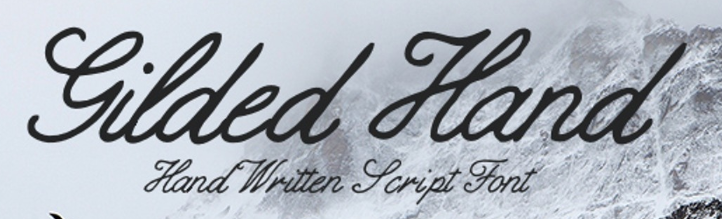
このリストの最初のフォントは文字通り手作業で作成されたものであり、これを見ると明らかです。 それは古い羊皮紙で場違いに見えない書体であり、華やかなスタイリングにもかかわらず、その筆記体の性質は読みやすく、4ドルで悪くはありません。
ただし、Gilded Handは小さいサイズでは少し読みにくい場合があるため、これはタイトルと見出しにのみ使用することをお勧めします。 ただし、サイズの小さい筆記体スクリプトは読みにくいことが多いため、これは予想されることです。
2.ボールペン
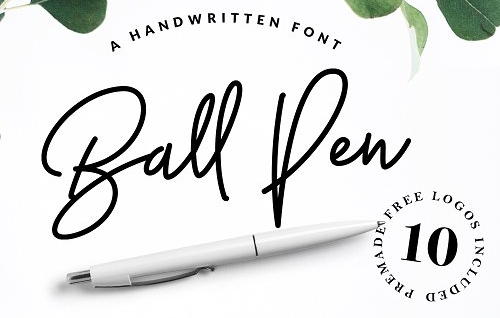
次に、ボールペンは手書きの「ヒップスター」スタイルのフォントで、クラシックとモダンの両方を同時に見ることができます。 私たちは特に白の見た目が大好きで、あなたのデザインに気楽なスタイルを与えることができます。
作者は、すばやく書き留められた署名を呼び出す方法を高く評価するかもしれませんが、これはヴィンテージのロゴで自宅にぴったりと見えると思います。 Gilded Handと同様に、これは超大型のタイトルや潜在的にコールアウトテキストなどのアプリケーションに使用することをお勧めします。
3.デイジードッグ
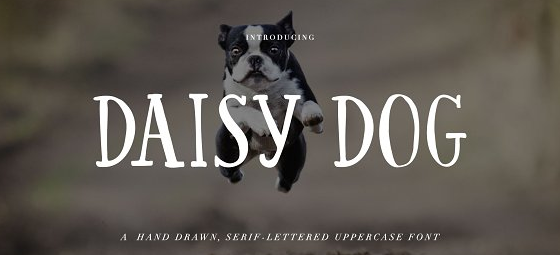
デイジードッグはヴィンテージ風で、このオールキャップスフォントは簡単にスタイリッシュです。 また、ヘッダー画像、タイトル、ロゴの優れたオプションとなるデザインにより、非常に読みやすくなっています。
ボールペンと同じように、このフォントも白で非常に上品に見えます。つまり、背景が暗いサイトでは、これを確認する必要があります。 デイジードッグはオールキャップスであるため、一般的な本文テキストには適していませんが、コールアウトやその他の目立つテキスト用の場所を見つけることができる可能性があります。
4.作成者タイプ
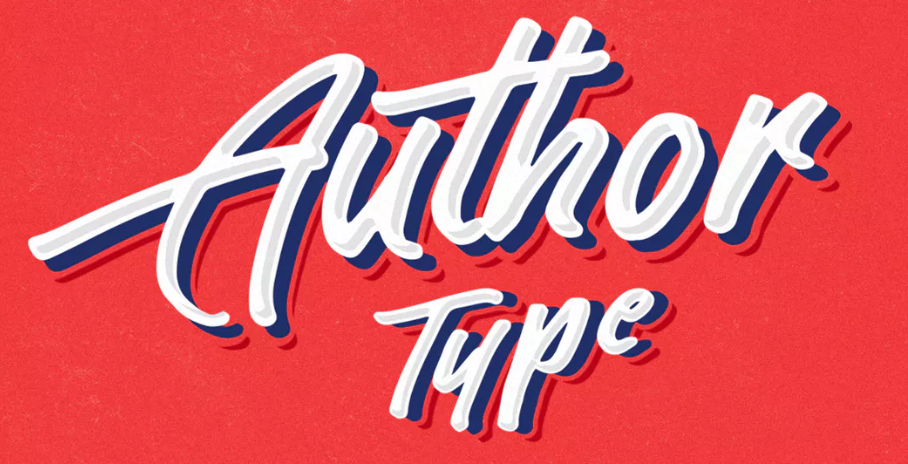
著者タイプは、古い漫画本に見られる、またはヴィンテージのストリートウェアに飾られていると予想される種類のフォントです。 昔ながらの50年代の魅力を漂わせ、ドロップシャドウのおかげで、サイトに少し奥行き感を与えます。
フォントの使用に関しては、AuthorTypeは特にカラフルなデザインの中で家にいるように見えます。 ただし、特に太字またはモノクロのパレットを使用する場合は、ロゴにも特に優れたオプションです。
5.上品さを保つ
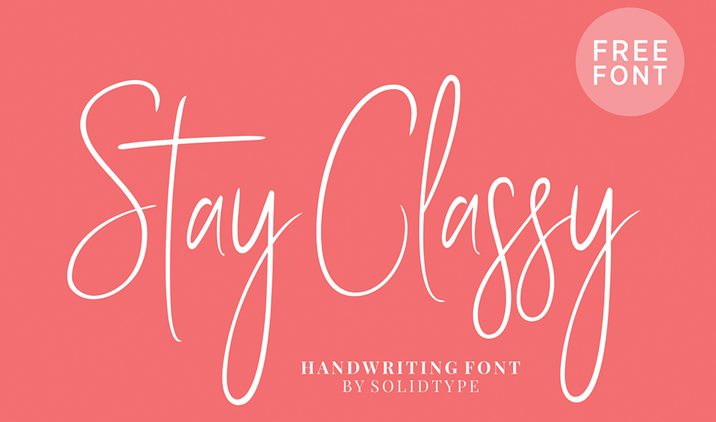
アンカーマンのロンブルゴーニュよりもはるかに洗練された状態で到着したStayClassyは、書道家の夢のように見えます。 文字は背が高くて細く、テキストに優雅さを与えます。その半筆記体の性質は、読むときに「動き」と先頭の行を提供します。
この書体をロゴ内で、そしてスタイルを呼び出す必要がある場所で試してみることをお勧めします。 ソーシャルイベントのウェブサイトはStayClassyに適していると私たちは主張しますが、ママのブロガーはこれが白い背景にパステルカラーでどのように見えるかを喜ぶでしょう。
6.喜び
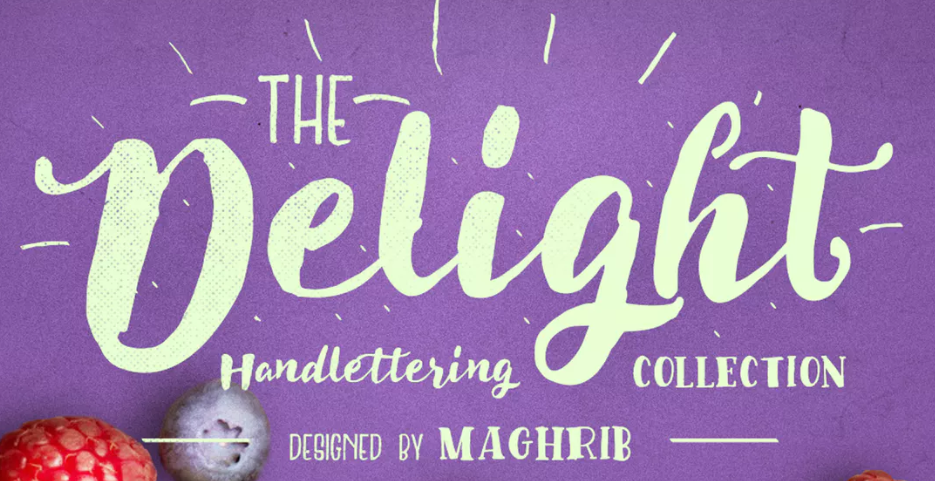
他のフォントには明確な焦点がありましたが、TheDelightのスタイルを特定するのは困難です。 ヴィンテージのポスターや、過ぎ去った印刷広告に見られるようなレタリングフォントを参照しています。
言い換えれば、The Delightはレトロな魅力がすべてであり、結婚式の招待状の見出しなど、デザイン全体にそびえ立つタイトルに最適です。 食品のウェブサイトもこのフォントに適している可能性があります。「斑点」と華やかな要素には、いわば「こぼれたクリーム」のわずかな感覚があるからです。
7.アドベンチュラ
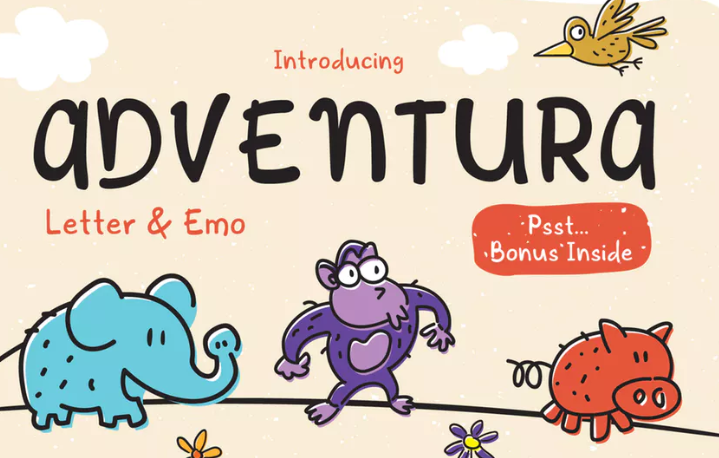
アドベンチュラは、手書き文字と幼稚な精神を組み合わせた結果です。 このリストにある他の多くのフォントとは異なり、サンセリフで筆記体ではなく、ある程度の動きはありますが、「ブロック状」の外観を提供します。
子供向けの本の表紙や、イラストの上にテキストを追加する必要がある場合に最適な組み合わせです。 それは気まぐれですが、それでも非常に読みやすく、そうでなければ正式なニッチのより非公式なサイトにさえ適しているかもしれません。 全体的に、それはあなたがいくつかの非常に楽しいデザインを作成するのを助けることができます。
8.ビッグバン
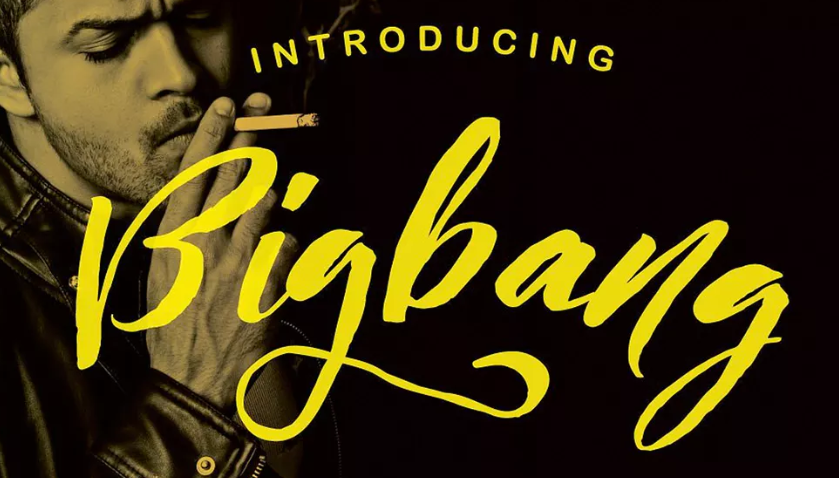
「理由もなく反逆者」と叫ぶ手書きフォントを探しているなら、Bigbangがぴったりです。 その汚れたスタイルは、それがブラシストロークを使用して書かれたように見え、はっきりと個人的なタッチを提供します。
ただし、全体的な形状は、それがデザインを支配する種類のフォントであることを示唆しているため、ロゴやインパクトのあるヘッダーには使用することをお勧めします。 「ヒップスター」のウェブサイトにも、ウィッシュリストに追加する別のフォントがあります。
9.オーテニア
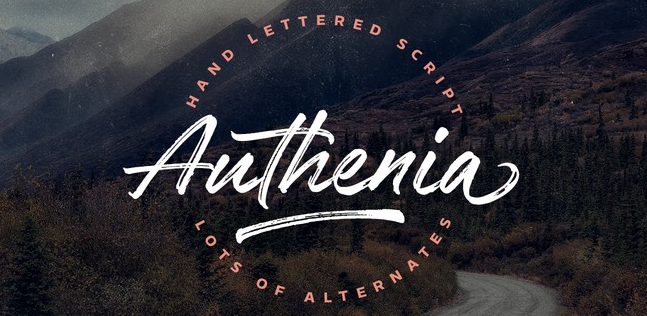
別の半筆記体フォントの例であるAutheniaは、筆記体に基づく単純なオプションです。 それはほとんど「触ることができる」そして深さと動きの両方を提供する素敵なテクスチャーを持っています。
のんびりとイタリック体になっているので、ヴィンテージのTシャツやアウトドアアクティビティに合わせて作られた書体のようなものです。 また、特に代替フォントが含まれている場合は、プライマリロゴフォントとして試してみることをお勧めします。
10.オルガニカ
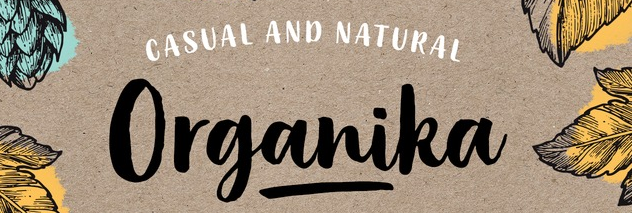
名前が示すように、Organikaはすべて自然な文体に関するものです。 筆記体で不規則な形であるにもかかわらず、読みやすいカジュアルなフォントです。 このリストの他の選択肢と同様に、このため、より大きなサイズでより適切に使用されるようになります。
有機ジャムの瓶の上で場違いに見えない書体を探しているなら、これは完璧に合うかもしれません。 ただし、その「ヒッピー」スタイルに惑わされないでください。Organikaはそのデザインに多くの考えを持っており、料理関連のサイトや個人のブログのために天国で作られたマッチです。
11.晴れの日
クラシックなキャデラック、ジュークボックス、モルトショップの考えを呼び起こすフォントを探しているなら、Finedayがリストの一番上にある可能性があります。 また、その太いブラシストロークと悪魔のようなケアのスワッシュは、はっきりと赤い種類のコーラのロゴに似ていることに気付くかもしれません。 このフォントは、筆記体と非筆記体のレタリングを選択できるため、ほとんどのフォントよりも柔軟性があります。
ニッチに思えるかもしれませんが、パロディーデザインに取り組んでいる場合は、これが最初の投票用紙のフォントの選択になります。 ただし、レストランのWebサイトや古着のロゴなど、単独で使用することもできます。
12.美しい人々
最後のいくつかのフォントについては、Billy Argelファウンドリを見ていきます。これは、レタリングフォントの優れた例がいくつか含まれているためです。 たとえば、Beautiful Peopleは、白黒の映画に対して「エンドクレジット」の感覚を持っており、すぐに高級感を与えます。 それは美しい筆記体ループと非常に狭い文字間隔を特徴としています。 これは、最も目立つサイズ以外では、読みやすさが問題になる可能性があることを意味します。
私たちの意見では、BeautifulPeopleは美容ウェブサイトや結婚式の招待状に最適です。 また、これをパロディーデザイン、または訪問者がハリウッドの黄金時代に関係する必要がある状況で再び使用することもできます。
13.トマト
リストの前半で「署名」スタイルのフォントを見てきましたが、ここに別の例があります。 トマトはサインのような感触があり、「ぎこちない」品質ですが、それでも読みやすくなっています。 また薄いので、このフォントを大きくしたいと思うでしょう。
手書きに基づく他のレッティングフォントと同様に、Tomatoesは、人間の手で作成されたテキストを偽造する必要がある場所に最適です。 著者のウェブサイト、著名なサインオフなどを考えています。
14.一口チョコレート
最後から2番目のフォントは、フランスのチョコレートラッパーに見られるレタリングのスタイルと非常によく似ています。つまり、非常に上品です。 Bite Chocolateにはたくさんの動きと選択肢がありますが、その主な強みは柔軟性の欠如であると私たちは主張します。
別の言い方をすれば、これは食品関連のデザインや、気まぐれなルックスの場合に考えられるでしょう。 筆記体のスクリプトを使用した他のデザインにこれがどのように適合するかはわかりませんでしたが、もちろん、特定のアプリケーションが重要です。
15.カサンドラ
大事なことを言い忘れましたが、Cassandraは、香水広告やファッション雑誌で見違えることのないようなデザインを特徴としています。 いくつかの優れた代替手段やその他の追加機能があります。つまり、1つのことを非常にうまく実行しながら、柔軟性を提供します。
全体として、それは1つのパッケージにヴィンテージで現実的です。 ロゴのデザインに最適だと思いますが、その繁栄を抑えてタイトルや見出しにも使用できます。
結論
フォントには、あらゆる形状、サイズ、アプリケーションがあります。 レタリングフォントがより専門的な選択と間違われることは決してありませんが、それらは作家的または気まぐれなサイトデザインを探している人のための単なるチケットになるでしょう。 彼らは特に個人的なタッチを持っていますが、間違ったものを選ぶと印象が悪くなる可能性があります。
私たちのお気に入りのレタリングフォントは、簡単にエレガントです。 たとえば、GildedHandはその名前が聞こえるほど派手です。 対照的に、BallPenまたはStayClassyは、個人のブログに合うように署名スタイルの空気を放ちます。 Adventuraなどの例を見つけることもできます。これは、若い訪問者に焦点を当てたWebサイトや、その他の非公式なビジネスに最適です。